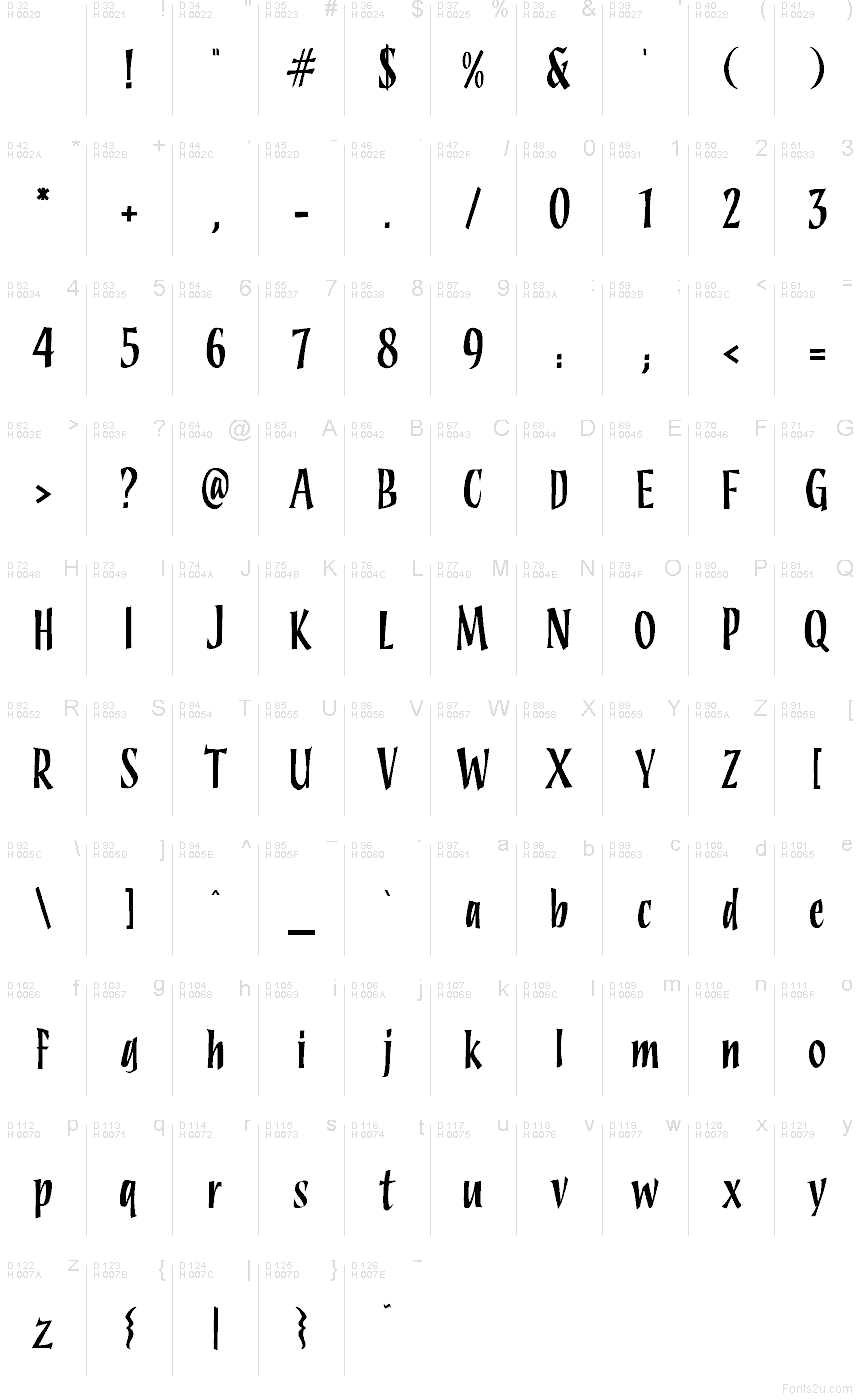
My Lovely Witch de BlackFridayFont es una tipografía serif gratuita con un toque espeluznante inspirado en los libros de cuentos de Halloween. Las letras se inclinan y oscilan con formas altas y comprimidas, pies afilados como cuñas y un ritmo ligeramente irregular que resulta más encantado que terrorífico.
Ideal para titulares de carteles, invitaciones, packaging de temporada, portadas de libros y gráficos de eventos temáticos donde buscas una pizca de travesura teatral sin llegar al terror explícito. Al ser estrecha, angulosa e irregular de forma deliberada, también funciona de maravilla en tarjetas de título, etiquetas y branding con un estilo de cuento oscuro y brujesco.